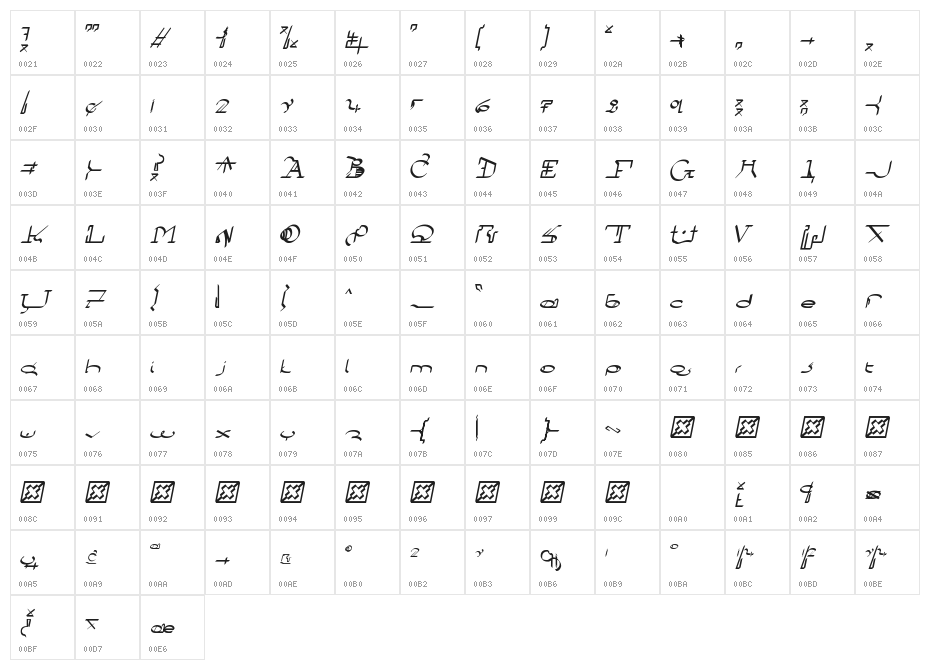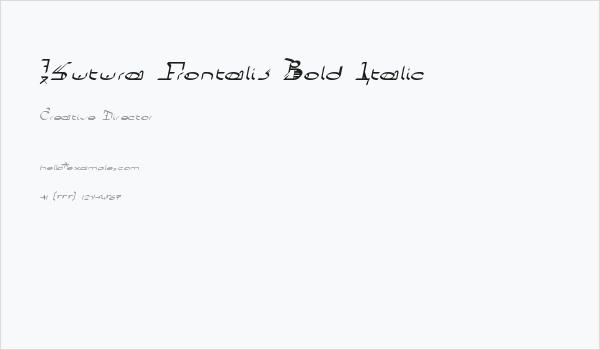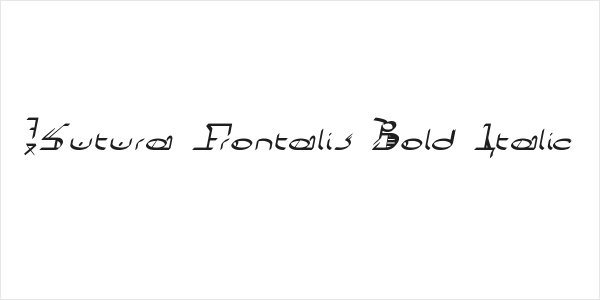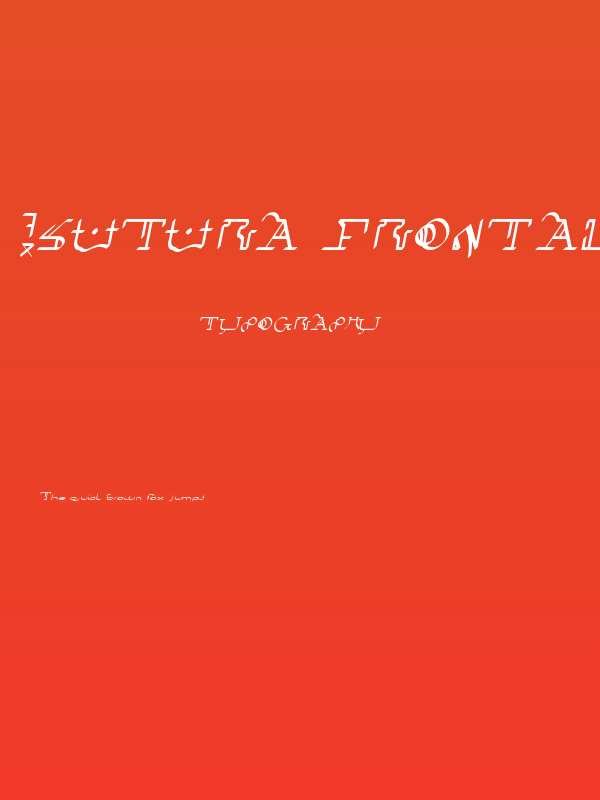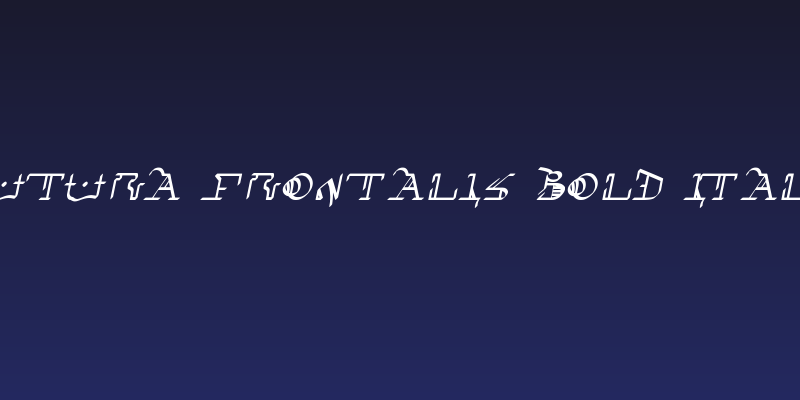
!Sutura Frontalis Bold Italic Font
| Progetti proposti | Ideal for sci-fi themed projects, modern branding, edgy posters, and innovative product packaging. |